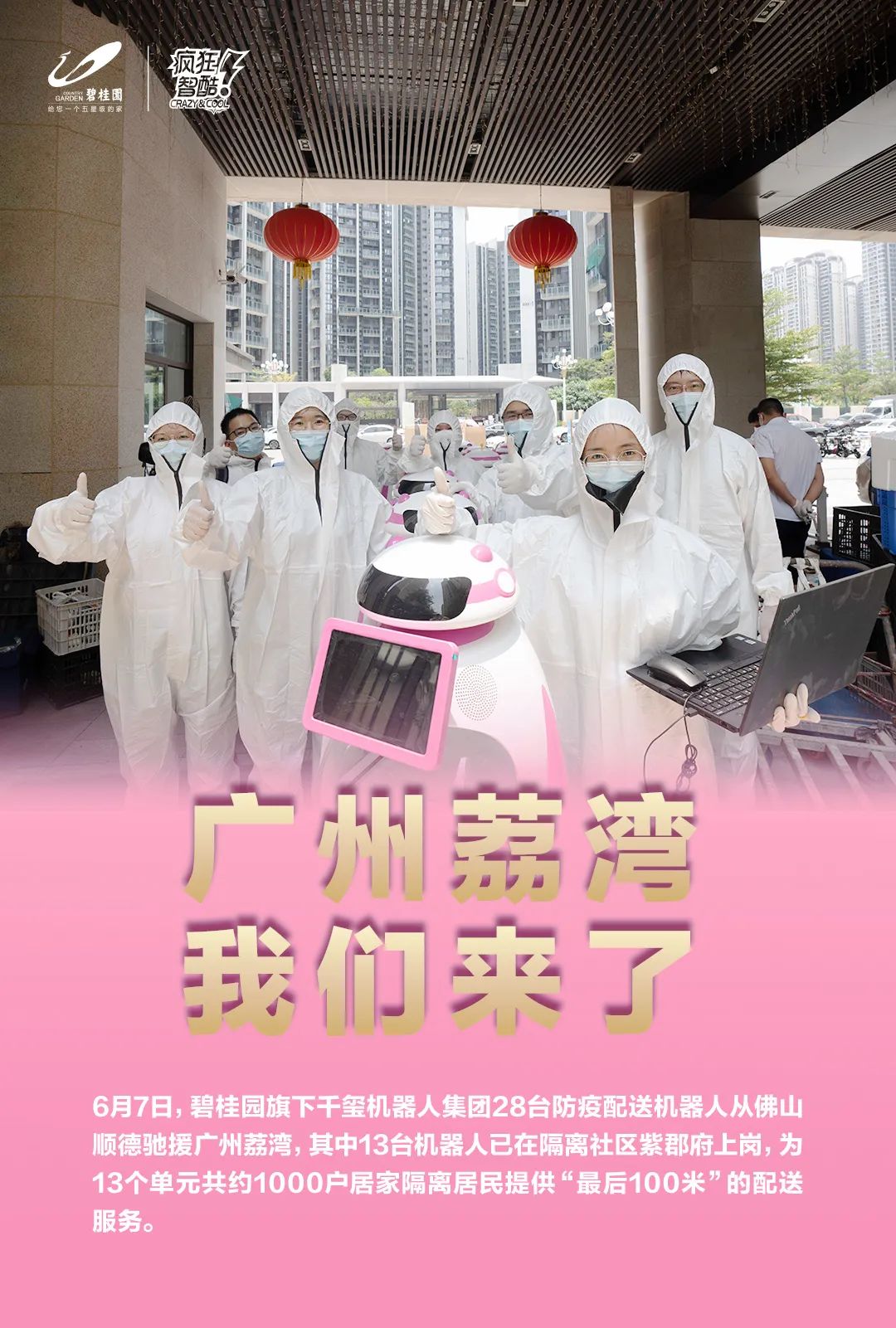
方正醒黑家族
梅花
黑体、混合、创意字体
2022
醒黑这款字属于黑体家族,区别于传统黑体直角硬朗的风格,部分笔画的起笔改为斜圆,让原本封闭的结构断开,增加了柔和感。点画和勾画的不等粗处理及横画收笔的斜切,又增加了趣味感。拐角处增加的饰线与横竖风格呼应,形成了统一。这款字体共6个系列,适合多种媒介平台的标题和正文使用。